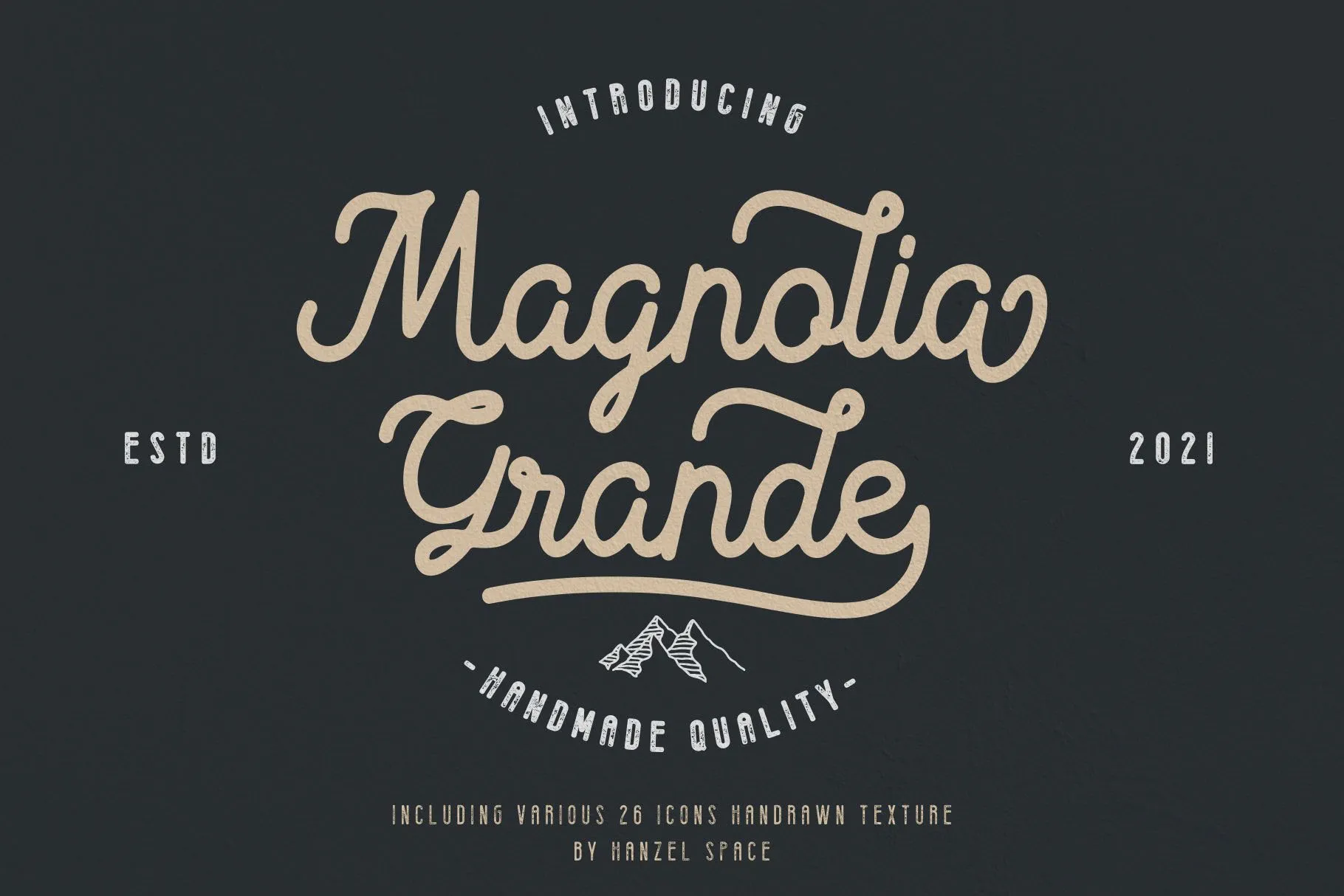
Magnolia Grande Font – Download Grátis
A Magnolia Grande Font é uma elegante tipografia vintage criada pelo designer Hanzel Studio. Inspirada nos muros de azulejos antiguidade que decoravam as casas no Brasil, esse tipo de letra é perfeito para criar logotipos e designs de embalagens com um toque de personalidade única. Além disso, a fonte inclui uma coleção diversificada de 26 ícones desenhados à mão, facilitando ainda mais a criação de logos e selos. Esta opção vintage e artesanal certamente tornará qualquer design elegante e único. Com Magnolia Grande Font, você pode transportar seu projeto para um novo estágio de sofisticação e originalidade.